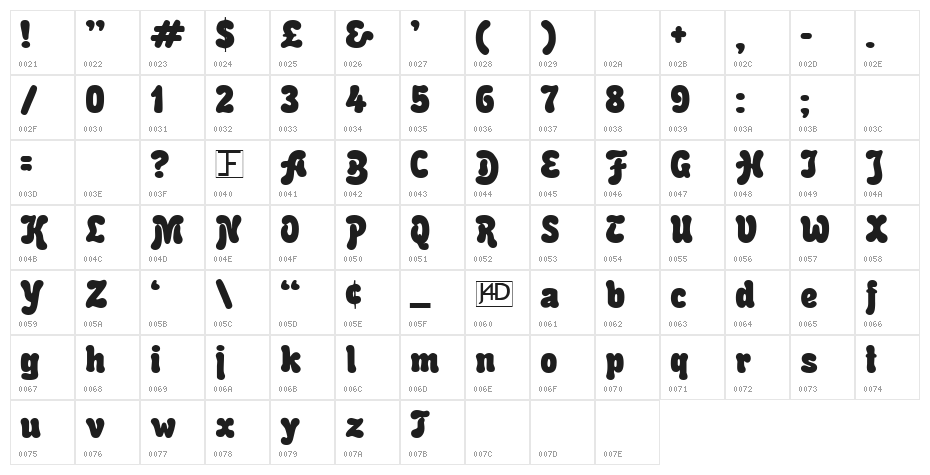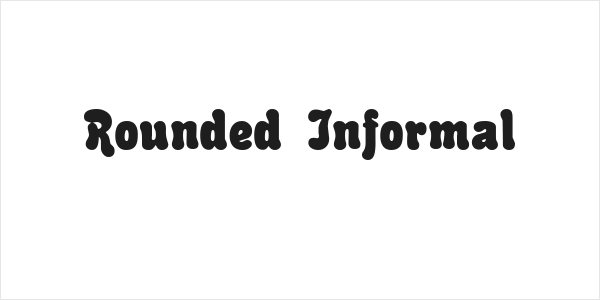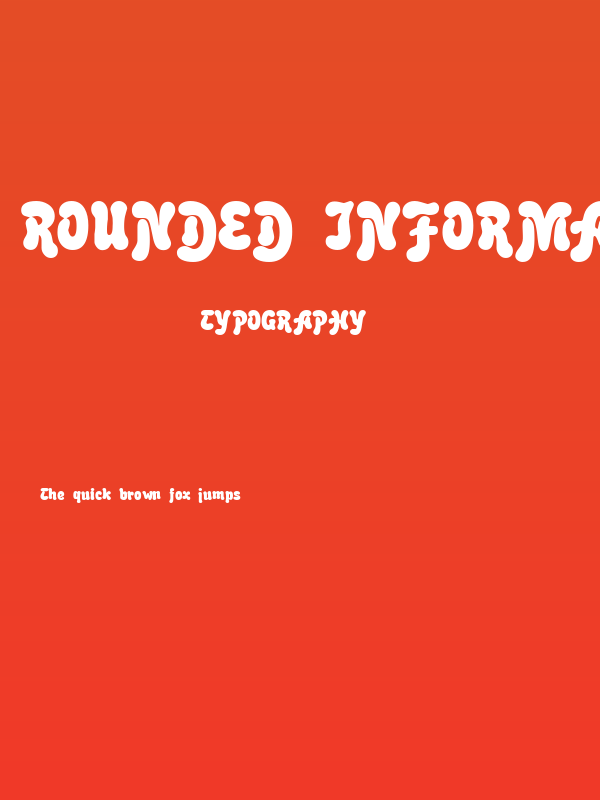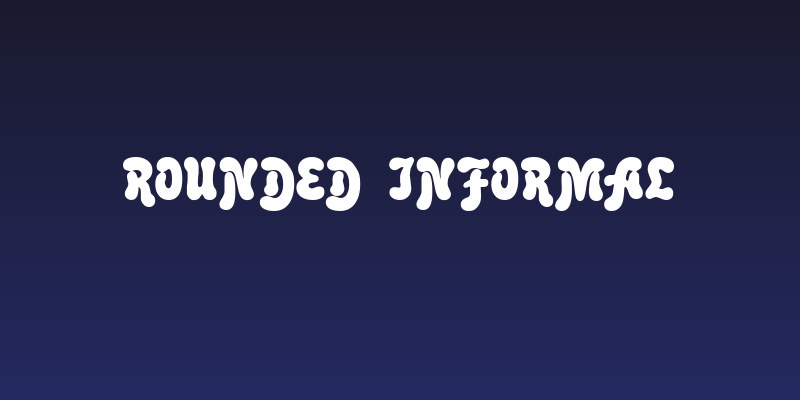
Rounded Informal Font
James Fordyce
| Stile generale | Playful, Casual |
| Progetti proposti | Ideal for children's books, playful branding, casual invitations, and fun posters. |